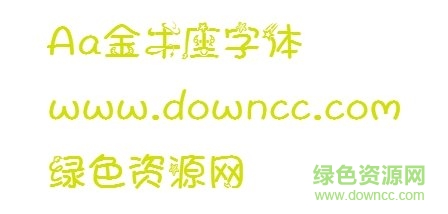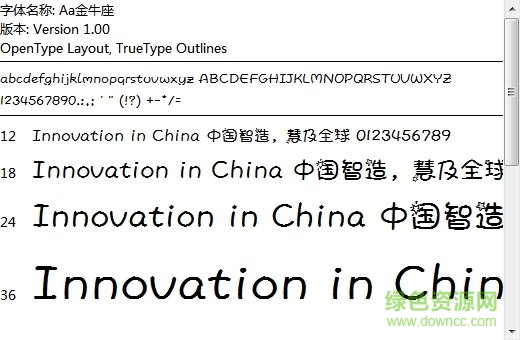
金牛座專屬字體是專為金牛星座的朋友打造的個(gè)性化的可愛字體,點(diǎn)綴不是很多,讓文字更容易辨認(rèn)和閱讀,字跡圓潤(rùn),讓文字擁有不一樣的美感,綠色資源網(wǎng)今日推薦!
金牛座是很保守的星座,喜歡穩(wěn)定,不愛變動(dòng)。
在性格上則比較慢熱,對(duì)工作、生活、環(huán)境都需要比較長(zhǎng)的適應(yīng)期。
Aa-金牛座以胖丫兒為打底字,加入牛尾牛角等可愛小元素,更加生動(dòng)形象。
金牛座字體是aa字體推出的十二星座系列字體之一,都是在胖丫兒字體上進(jìn)行美化修飾而來(lái),字跡明亮清秀,適合于排版印刷、廣告創(chuàng)意、平面設(shè)計(jì)等多個(gè)方面。